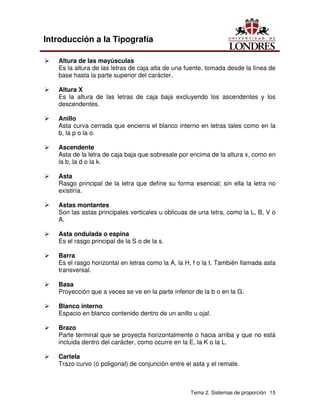
Introducción a la
Tipografía
Introducción
El significado de un mensaje ha de hablar en el interior de formas, de llenos y
vacíos construidos geométricamente, con las correcciones ópticas necesarias para
que la lectura sea clara y racionalmente comprensible.
La tipografía es un conjunto de reglas proyectuales y, sobre todo, en cuanto a
lugar de elaboración de la cultura, a través de la cual los hombres están en
condiciones de emanciparse, respecto de otras manifestaciones lingüísticas.
La lengua no es una forma, representa un contenido que es el resultado de
conflictos, también de dramas y de violencia, de encuentros y desencuentros... la
Historia.
Escribir sobre un alfabeto implica que mientras lo hacemos estamos echando
mano a él mismo para transmitir nuestras ideas. Así como los lectores lo usan
para entender lo que se dice. Se aplica un código habitual, aprendido. Estamos
habituados a verlo como herramienta donde «leer» y con el cual «escribir».
Es así que se nos hace invisible a menos que se nos muestre como presente,
haciendo notar las peculiaridades estructurales de esta o aquella letra, las
posibilidades de armónica proximidad y, más aún, las dotes de perceptibilidad, de
legibilidad, de fluidez de un texto compuesto con aquel determinado carácter.
Que el carácter tipográfico trascienda su propio valor instrumental, para
proponerse como entidad sígnica autónoma, no es una cosa nueva, por el
contrario, sobre el contenido estético – formal del signo alfabético existen tratados
históricos.
Así que este boom por el uso de la tipografía como forma no es nada nuevo.
Objetivo general
Al término del curso el estudiante transcribirá a proyectos de diseño gráfico los
principales elementos de la composición y adecuación tipográfica a partir del
análisis de sus características y procedimientos así como las necesidades del
proyecto.
Calculará y proporcionará las diferentes fuentes y familias tipográficas de acuerdo
con las necesidades de comunicación del mensaje a elaborar.
Tema 1. El tipo
Subtemas
1.1 Definición
1.1.1 Definiciones de tipografía
1.2 Elementos anatómicos
1.3 Estilos y personalidad del tipo
1.4 Clasificación
1.4.1 Familias tipográficas
1.4.2 Fuentes tipográficas
1.4.3 Series
Objetivo de Aprendizaje
Al término del tema el estudiante distinguirá lo que es un tipo, una fuente y una
familia tipográfica y entenderá su importancia en la transmisión de mensajes.
Introducción
La Tipografía como disciplina del Diseño Gráfico estudia los distintos modos de
optimizar la emisión gráfica de mensajes verbales. El diseñador gráfico en su
tarea cotidiana debe conocer las familias tipográficas para poder expresar
correctamente la idea que requiere conceptuar.
1.1 Definición
Tipo es el objeto físico, un bloque paralelepipédico de metal (aleación tipográfica)
que tiene en su cara superior, en relieve e invertida, la imagen de una letra o signo
para la impresión por sistema tipográfico.
1.1.1 Definiciones de tipografía
En nuestra tarea cotidiana, Tipografía admite cuatro definiciones:
1) La primera de ellas, referida al origen de la palabra tipografía se emplea para
designar a la técnica de impresión con tipos móviles que; procedente de Asia,
llegó a Europa a mediados del siglo XV;
Tema 1. El tipo 7
Introducción a la Tipografía
2) La segunda, impuesta por los avances tecnológicos, extiende los alcances de
la primera definición y denomina tipografía a todas las modalidades de
reproducción de palabras y textos de la actualidad;
3) La tercera, aplicada en ámbitos académicos, denomina Tipografía a la
materia en que se desarrollan los contenidos históricos, teóricos y prácticos
referidos al elemento con que se representan visualmente las palabras y los
textos.
4) La cuarta acepción es la más abarcativa, se emplea recientemente en el
ámbito profesional del Diseño Gráfico y es la que más nos interesa:
denomina Tipografía a la disciplina que dentro del Diseño Gráfico estudia los
distintos modos de optimizar la emisión gráfica de mensajes verbales. La
Tipografía tiene una dimensión técnica y funcional basada en el oficio de
tipógrafos e impresores. Cuenta con sistemas de medición y cálculo que
ayudan a organizar y racionalizar la comunicación visual. Pero tiene además
una dimensión humanística que se basa en la escritura, representación
abstracta de objetos e ideas que hizo posible el registro de la cultura, la
organización del pensamiento y el desarrollo intelectual del hombre.
Entendida como disciplina, la Tipografía profundiza y enriquece en
direcciones múltiples los alcances del Diseño Gráfico.
1.2 Elementos anatómicos
La temprana asociación entre las letras y la forma humana y sus movimientos ha
ejercido cierta influencia en el pensamiento creativo. Estas similitudes
estructurales, que tienen su origen en las leyes de la naturaleza, liberan a las
letras de su bidimensionalidad y las pone en movimiento haciéndolas participar
activamente dentro de la composición.
Hablar de anatomía del tipo es hablar de la forma de la letra, de sus detalles más
íntimos, de la manera en que cada una de sus partes ha sido moldeada y
reinterpretada a través del tiempo. Debido a que la forma de una tipografía tiene
un gran impacto sobre la función que esta cumple, es importante conocer como la
presencia o ausencia de ciertos elementos pueden afectar a una determinada
familia de tipos, y por ende al texto en el cual es usada.
Desde sus orígenes los caracteres han sufrido una constante transformación, de lo
antiguo a lo moderno, de lo sobrio a lo exagerado, de lo orgánico a lo sintético.
Durante este proceso han recibido infinidad de aportaciones, muchas veces
dependiendo del contexto histórico, político, económico y social del que formaban
parte. Es gracias a estas características que podemos clasificar las tipografías,
aun cuando surgen ciertos conflictos para llevar a cabo dicha tarea.
Tema 1. El tipo 8
Introducción a la Tipografía
La aplicación indiscriminada de términos ha provocado que el estudio de la
tipografía se dificulte, algunos conceptos han logrado alcanzar cierta
estandarización.
1.3 Estilos y personalidad del tipo
Desde fines del siglo XIX hasta principios del siglo XX, los símbolos del desarrollo
industrial y la maquinaria utilizada para su creación se expresaron vívidamente en
la arquitectura, la pintura, la fotografía, el cine y la escultura, así como en los
medios publicitarios. La influencia de esta revolución industrial y las cambiantes
orientaciones políticas estimularon el desarrollo de movimientos artísticos como el
futurismo y el constructivismo. Los artistas y los diseñadores innovadores
propagaron la creación de poderosas imágenes visuales que reflejaron el espíritu
vibrante de la época. Desde la época de Gutenberg, la fundición de tipos fue el
principal método de composición. Sin embargo, hacia fines del siglo xix, la
composición manual que utiliza tipos fundidos fue reemplazada por la introducción
de máquinas de composición tipográfica que permitían grabar los caracteres
directamente en el taller tipográfico.
Relación de la tipografía con la escritura. Influencia de los orígenes históricos de
las formas escriturales sobre las familias tipográficas modernas.
Esquema de la evolución histórica de la escritura. Cuatro fases:
- Semasiográfica
- Pictográfica
- Fonográfica
- Hipergráfica
Evolución de las formas fonográficas según un modelo (no paradigmático) de
etapas:
- Jeroglíficas
- Silábicas – Protoalfabéticas
- Alfabéticas
Evolución histórica de los alfabetos y de su uso social hasta el presente.
- Alfabetos griegos
- Alfabeto romano
- La escritura medieval
- Renacimiento e invención de la imprenta
Tema 1. El tipo 9
Introducción a la Tipografía
- Ilustración. Siglo XVIII ILUSTRACIÓN
- Litografía y composición en caliente
- Composición electrónica SIGLO XX
Familias tipográficas. División en subfamilias según el trazo, los ejes y las
proporciones.
- Superfinas, finas, medium, negras, supernegras...
- Rectas, cursivas retrógradas...
- Redondas, chupadas o condensadas, expandidas o anchas...
- Perfiladas, sombredas.
1.4 Clasificación
1.4.1 Familias tipográficas
Una familia tipográfica es un grupo de tipografías unidas por características
similares. Los miembros de una familia (los tipos) se parecen entre si, pero
también tienen rasgos propios. Las tipografías de cada familia tienen distintos
grosores y anchos. Algunas familias las forman muchos miembros, otras sólo de
unos pocos.
En resumen una familia tipográfica se define como un conjunto de letras de
cualquier tamaño y estilo que tienen el mismo diseño común. Una fuente
tipográfica (font) es un alfabeto completo dibujado en un solo tamaño y un solo
estilo.
1.4.2 Fuentes tipográficas
La palabra fuente se utiliza actualmente para describir todos los elementos
anteriores más las cursivas, finas y negras de la misma familia de tipos. Una
tipografía está compuesta por los conjuntos de caracteres representados por todos
los tamaños y grosores de una determinada clase de letra.
Cada tipo era un bloque metálico paralelepipédico de 2,5 cm de longitud que
llevaba en una de sus caras una letra o un carácter en relieve. Las líneas de tipos
se componían, se entintaban y se colocaban en la prensa de imprimir que oprimía
el tipo contra el papel u otro tipo de soporte, produciendo una imagen legible.
Aunque la época de mayor auge de los tipos metálicos y la impresión en relieve
quedó atrás hace tiempo, la palabra tipo sigue describiendo un carácter de
impresión independientemente del material, ya sea éste metal, película o soporte
Tema 1. El tipo 10
Introducción a la Tipografía
magnético, o incluso esté almacenado en forma de una serie de fórmulas
matemáticas en una computadora.
En autoedición, los términos tipografía y fuentes a menudo se confunden como
sinónimos; sin embargo, la tipografía es el diseño de caracteres unificados por
propiedades visuales uniformes, mientras que la fuente es el juego completo de
caracteres en cualquier diseño, cuerpo y estilo.
Estos caracteres incluyen letras en caja alta y baja, numerales, versalitas,
fracciones, ligaduras (dos o más caracteres unidos entre sí formando una sola
unidad), puntuación, signos matemáticos, acentos, símbolos monetarios y
grafismos (adornos variados y florituras diseñados para su uso en las fuentes)
entre otros. Aunque, para autoedición, la totalidad de los caracteres citados suelen
estar en las fuentes denominadas «expert».
1.4.3 Series
Por su naturaleza de multiplicidad estilística, la familia tipográfica serial nos
propone una manera particular de abordar el diseño de caracteres. Un repaso
sobre los diseños más influyentes, considerados en su contexto histórico, deja
abiertos algunos interrogantes y controversias para la discusión.
Demos fue diseñada en 1976 para el sistema de fotocomposición Digiset Gerard
Unger dibujó manualmente signo por signo en una matriz de 100 puntos
horizontales por 120 en vertical.
El programa de Rotis fue manufacturado por Agfa Compugraphic en 1988. Como
caracteres distintivos en el diseño en general se destacan la c y la e, esta última
por su altísima cintura.
La familia serial y la clasificación de tipos. La idea de abordar un grupo específico
de tipos dentro del vasto universo de familias tipográficas parece exigir una
justificación inmediata. De hecho, el argumento podría entenderse como el
artilugio esencial del acto -taxonómico si los hay- de clasificación de tipos: ¿Cómo
agrupar especies comparando sus cualidades constitutivas? Sin embargo, ya que
esto puede considerarse desde varios aspectos: históricos, tecnológicos o (más
frecuentemente) estilísticos, la clasificación resultante termina involucrando
también un criterio particular de aproximación al problema.
La historia de la clasificación de tipos podría pensarse de este modo como la
historia de los intentos sucesivos por organizar la variedad de formas tipográficas
desde un punto de vista innovador. Se calcula en la actualidad entre 8.000 y
11.000 el número de tipografías conocidas. Es claro que la continua aparición de
nuevas familias en ambos campos, texto y display, desestima la idea de una
Tema 1. El tipo 11
Introducción a la Tipografía
taxonomía definitiva y más bien nos lleva a pensar que la clasificación de tipos es
algo vivo que reclama un espíritu de constante revisión. Pero el título de este
artículo es también el resultado de un discernimiento particular sobre
determinadas familias tipográficas de acuerdo con su pertenencia a un pequeño
universo. Este universo parece tocar preliminarmente conceptos como: familia,
subfamilia y superfamilia, interrelación, declinación, alternación, programa, serie.
Sería posible decir, sin embargo, que esos conceptos son inherentes al diseño de
toda tipografía, desde que cada letra individual es como una nota en armonía con
el resto de la melodía o, en palabras de Sumner Stone, «una variación sobre un
paso de danza básico». Aunque más aparente, este aspecto, sutil herencia de la
mano de calígrafos y escribas, es aún constitutivo del diseño de tipos en términos
de ritmo y uniformidad: cada signo ha sido construido por la misma herramienta o,
al menos, existe un principio común que gobierna la consistencia formal de todo el
alfabeto.
Tema 1. El tipo 12
Introducción a la Tipografía
Resumen
El tipo básicamente es un caracter de impresión, una tipografía está compuesta
por los conjuntos de caracteres representados por todos los tamaños y grosores
de una determinada clase de letra los cuales son indispensables en el diseño
gráfico. Los tipos se pueden clasificar en fuentes, familias y series, para lograr
estas clasificaciones nos vamos a aprovechar de sus rasgos característicos y
estilos.
Conclusión
La clasificación de los tipos y sus características nos va ayudar a identificarlos y
poder expresar la idea o mensaje que queramos o necesitemos.
Tema 2. Sistemas de proporción 13
Introducción a la Tipografía
Tema 2. Sistemas de proporción
Subtemas
2.1 Concepto
2.2 Estructura
2.3 Módulo X
2.4 Light, bold, espesor
2.5 Romanas e itálicas
Objetivo de Aprendizaje
Al término del tema el estudiante conocerá las diferentes partes de una letra
Introducción
Es importante conocer los sistemas de proporción y la terminología que hace
referencia las diferentes partes de una letra.
2.1 Concepto
Los sistemas de proporción nos van permitir construir una tipografía a partir de
un tipo y sus características para esto vamos a tener que tomar en cuenta ciertos
elementos que veremos a continuación dentro de este capítulo.
Lo más importante de la elección de cualquier medida tipográfica es que esté en
relación con las que ya se han tomado o tienen que tomarse.
Ninguna medida tipográfica es independiente de las otras.
• Del tamaño del cuerpo depende la línea
• De la longitud de la línea depende la interlínea
• De las interlíneas depende la coherencia del párrafo, etc
Hay que considerar, además, que muchos diseños tipográficos requieren un
particular tratamiento, al cual el diseñador tiene que ser sensible.
• Algunas familias requieren ser usadas en cuerpos grandes porque si no, no
se aprecia su diseño
Tema 2. Sistemas de proporción 14
Introducción a la Tipografía
• Lo mismo al contrario: letras de proporciones estrechas, muy espigadas,
pueden ser fatigosas cuando se usan a razón de 150 caracteres en líneas
que tal vez no son demasiado largas, pero que cansan al lector. La
proporción del diseño de la letra y de la línea, no cuadran entre sí.
2.2 Estructura
El vocabulario usado para la descripción de las diferentes partes que estructuran
una letra, se compone de una serie de términos acuñados desde hace mucho
tiempo y que se asemejan a los usados para describir las partes de nuestro
cuerpo. Así las letras tienen brazos, piernas, ojos, y otras partes como cola.
De cualquier forma, por problemas de traducción, la descripción de las partes de
una letra no coinciden de forma unánime en los libros sobre tipografía y diseño. En
todo caso los términos que aquí se reflejan constituyen un buen bagaje para
comprender y conocer las distintas partes de una letra.
Tema 2. Sistemas de proporción 15
Introducción a la Tipografía
Ü Altura de las mayúsculas
Es la altura de las letras de caja alta de una fuente, tomada desde la línea de
base hasta la parte superior del carácter.
Ü Altura X
Es la altura de las letras de caja baja excluyendo los ascendentes y los
descendentes.
Ü Anillo
Asta curva cerrada que encierra el blanco interno en letras tales como en la
b, la p o la o.
Ü Ascendente
Asta de la letra de caja baja que sobresale por encima de la altura x, como en
la b, la d o la k.
Ü Asta
Rasgo principal de la letra que define su forma esencial; sin ella la letra no
existiría.
Ü Astas montantes
Son las astas principales verticales u oblicuas de una letra, como la L, B, V o
A.
Ü Asta ondulada o espina
Es el rasgo principal de la S o de la s.
Ü Barra
Es el rasgo horizontal en letras como la A, la H, f o la t. También llamada asta
transversal.
Ü Basa
Proyección que a veces se ve en la parte inferior de la b o en la G.
Ü Blanco interno
Espacio en blanco contenido dentro de un anillo u ojal.
Ü Brazo
Parte terminal que se proyecta horizontalmente o hacia arriba y que no está
incluida dentro del carácter, como ocurre en la E, la K o la L.
Ü Cartela
Trazo curvo (o poligonal) de conjunción entre el asta y el remate.
Tema 2. Sistemas de proporción 16
Introducción a la Tipografía
Ü Cola
Asta oblicua colgante de algunas letras, como en la R o la K.
Ü Cola curva
Asta curva que se apoya sobre la línea de base en la R y la K, o debajo de
ella, en la Q. En la R y en la K se puede llamar sencillamente cola.
Ü Cuerpo
Altura del paralelepípedo metálico en que está montado el carácter.
Ü Descendente
Asta de la letra de caja baja que queda por debajo de la línea de base, como
en la p o en la g.
Ü Inclinación
Es el ángulo del eje imaginario sugerido por la modulación de espesores de
los rasgos de una letra. El eje puede ser vertical o con diversos grados de
inclinación. Tiene una gran importancia en la determinación del estilo de los
caracteres.
Ü Línea de base
La línea sobre la que se apoya la altura X.
Ü Ojal
Porción cerrada de la letra g que queda por debajo de la línea de base. Si
ese rasgo es abierto se llama simplemente cola.
Ü Oreja
Ápice o pequeño rasgo terminal que a veces se añade al anillo de algunas
letras, como la g o la o, o al asta de otras como la r.
Ü Rebaba
Espacio que queda entre el carácter y el borde del tipo metálico. Aunque se
suele nombar de esta forma, la definición correcta es "hombro".
Ü Serif, patin, remate o gracia
Trazo terminal de un asta, brazo o cola. Es un resalte ornamental que no es
indispensable para la definición del caracter, habiendo alfabetos que carecen
de ellos.
Ü Vértice
Punto exterior de encuentro entre dos trazos, como en la parte superior de
una A, o M o al pie de una M.
Tema 2. Sistemas de proporción 17
Introducción a la Tipografía
2.3 Módulo X
También conocido como altura x, distancia que alcanzan sobre la línea base las
letras minúsculas que no tienen trazos ascendentes ni descendentes
2.4 Light y bold, espesor
Otra propiedad de los tipos de letra tiene que ver con el espesor (ancho o peso)
de los tipos.
El espesor proporcional se llama así porque el ancho de los caracteres es
proporcional a su figura. Se supone que este espesor es el adecuado para el texto
base.
Estos ligeros cambios de espesor combinados con la inclinación del eje dan
origen a las familias: normal, cursiva, negrita o bold, ligera o light, demi-bold, extra
light y extra bold entre otros.
Cualquiera modos de espesor puede aplicarse a los dos estilos principales de los
caracteres, la letra romana o con patines y la letra paloseco o sin patines. Para los
estilos secundarios (manuscrita y fantasía), el espesor no es importante.
2.5 Romanas e itálicas
El alfabeto latino se remonta al imperio romano aunque sus orígenes son muy
anteriores con alfabeto con el tiempo los romanos desarrollarían un alfabeto a
través del etrusco, pero usando solo 21 de las 26 letras originales. Hubo 13 letras
que no variaron respecto de la de los griegos: A, B, E, H, I, K, M, N, O, T, X, Y y Z:
otras 8 letras fueron modificadas C, D, G, L, P, R, S, V y se restauraron otras dos
letras F y Q (que habían existido en el griego primitivo, pero se habían perdido en
el clásico.) Así pues, el alfabeto romano tenía 23 letras entre vocales y
consonantes, y con el los romanos lograron escribir una representación fonética.
De su lengua que hoy llamamos latín, las 3 letras adicionales- J, U y W – son
introducciones más recientes que se realizaron para representar otros sonidos.
Los romanos usaban la “I” para representar los sonidos de la “I y de la J y de la V
tanto para representar la U como la V la W se creo para representar un sonido en
ingles antiguo. Aunque el alfabeto romano adoptó numerosas formas, la capitales
quadrata (capital cuadrada) ha ejercido la máxima influencia en el desarrollo
tipográfico y de las escrituras de inscripción.
Tema 2. Sistemas de proporción 18
Introducción a la Tipografía
A la letra que tiene el eje inclinado se le llama itálica. Este término aplica igual de
igual manera para Romanas o San Serif, es decir fuentes con patines o sin
patines.
Tema 2. Sistemas de proporción 19
Introducción a la Tipografía
Resumen
En este capitulo el diseñador conoce el vocabulario utilizado para referirse a los
diferentes componentes de una letra así como los diferentes estilos.
Conclusión
Es importante que al referirnos a la tipografía conocer los antecedentes del
alfabeto latino así como las partes que constituyen cada una de las letras.
Tema 3. Adecuación tipográfica 20
Introducción a la Tipografía
Tema 3. Adecuación tipográfica
Subtemas
3.1 Concepto
3.2 Función
3.3 Características
3.4 Texto e imagen: Integración de dos formas de comunicación
Objetivo de Aprendizaje
Al término del tema el estudiante manejará diferentes técnicas y elementos para
comunicar mensajes a partir de textos y letras.
Introducción
La tipografía es un arte sutil. Se basa en pequeñísimas variaciones aplicadas a las
formas genéricas de las letras, que llevan por nosotros más de dos mil años. El
problema es que una pequeña modificación puede resultar de enorme efecto.
También es un arte sutil porque los elementos tipográficos han de conjugar entre
sí de manera muy delicada, y es suficiente con variar unos pocos parámetros para
que el proceso de lectura o de apariencia se altere.
Hay que añadir que el principio clásico que afirmaba que la tipografía sólo tiene el
deber de ser legible ha quedado desfasado. En términos generales la tipografía
tiene en la legibilidad el principal fundamento de su existencia, pero el plano
estético y de matización del simbolismo en la comunicación han cobrado una gran
importancia con la llegada de la tipografía digital.
3.1 Concepto
La Tipografía es uno de los diversos espacios del Diseño Gráfico cuyo objetivo
primordial es la producción de comunicación a través de la letra impresa. A la vez
que el diseño tipográfico debe satisfacer los requerimientos de transmisión de
información a partir de formas visuales, con el necesario conocimiento de las
pertinentes nociones ópticas, esta disciplina depende en la práctica de la relación
que se mantiene con las también posibilidades artísticas. La Tipografía requiere a
la vez experiencias de carácter plástico, en tanto que cada proceso de
configuración se acompaña de una expresión plástica.
Tema 3. Adecuación tipográfica 21
Introducción a la Tipografía
Se acotará básicamente la primera consideración de la Tipografía, determinada
por su finalidad práctica precisa: la transmisión de información a través de formas
visuales. Nos introduciremos en uno de los fines esenciales de la obra impresa por
medio de los signos de escritura, lo que implica uno de los campos de trabajo del
diseñador tipográfico: la configuración y coordinación del texto favoreciendo su
absorción por parte del lector.
La Tipografía, aparte de su función de optimizar la transcripción gráfica de sonidos
hablados, por medio de un sistema de signos convencionales, dota de un valor
expresivo al contenido del mensaje por medio de referencias formales en una
imagen. Se parte de la idea de la necesidad de atender al paralelismo existente
entre el contenido del texto y de su revelación en el espacio visual a través del
diseño tipográfico Factores que evidencian la problemática de la expresión
tipográfica serán la influencia de las nuevas tecnologías a la producción e
interpretación tipográfica, así como la necesidad de diferenciación y competencia
de nuestra sociedad industrial como factor de gestión empresarial a través de la
expresión verbal de la Identidad Visual Corporativa (logotipo). La Publicidad es
otro apartado en el que debemos penetrar ya que sus características específicas
exigen la unidad entre la palabra y la forma. Otros aspectos a tratar, de carácter
más general (problemáticas lingüísticas, requerimientos sociales, políticos e
ideológicos, ...), determinarán también a la Tipografía en sus valores visuales y
expresivos, ayudando al conocimiento de la “historia de la forma”.
3.2 Función
Tres elementos que parecen insoslayables a la hora de diseñar tipografía:
Ü Conocer
En principio es necesario adquirir el conocimiento de los múltiples aspectos
que la escritura y los caracteres tipográficos han asumido en los diversos
períodos.
Ü Ejecutar
El estudio en profundidad de los elementos estructurales del alfabeto y de las
leyes ópticas que gobiernan el dibujo de las letras y su composición, resulta
esencial a los fines de la reproducción correcta de los caracteres.
Ü Proyectar
A partir de las formas memorizadas y gracias a una técnica de ejecución
adquirida con paciencia, pueden afrontarse temas de proyección y de
investigación para el estudio de nuevos signos aptos para una comunicación
más fuerte y duradera.
Tema 3. Adecuación tipográfica 22
Introducción a la Tipografía
3.3 Características
El principio de jerarquía
La palabra Jerarquía no está de moda. Trae a la memoria viejos tiempos de
obediencia ciega y demasiada disciplina. Pero eso poco importa: una cosa es la
jerarquía social mal entendida, y otra muy distinta la jerarquía perceptiva y de
concepto, de la cual nos servimos para conocer mejor lo que nos rodea y para
comunicarnos.
La jerarquía, en términos de lógica visual, no es otra cosa que una manifestación
de las relaciones que se producen entre las cosas que vemos y entre las cosas y
nosotros mismos.
En este capítulo trataremos de los siguientes temas:
- El campo de la jerarquía en la percepción.
- Tipos de jerarquías naturales y culturales.
- El principio de anomalía perceptiva.
- Tipos de anomalías perceptivas.
- 10 ejemplos característicos de los conceptos explicados.
- Bibliografía.
El campo de la jerarquía en la percepción
La jerarquía es un principio de valor que presenta numerosas variables y se
produce en todo tipo de circunstancias.
Desde el punto de vista de la creación gráfica, es de particular importancia cuando
se considera en relación con la información que una persona recibe, ya que el
principio jerárquico hace que valore más aquello que le afecta o es de su interés.
El ser humano dispone de unas capacidades limitadas tanto en la percepción
como en el conocimiento. Necesita tiempo para asimilar y para comprender.
Incluso tiempo para ver, aunque esto apenas lo apreciemos. Mientras esto
suceda, los valores jerárquicos actuarán como un filtro que ordena la información.
Muchos de los valores que aplicamos en nuestra relación con el exterior son
aprendidos, otros son de tipo personal y otros tantos parecen tener profundas
raíces en nuestra naturaleza. Algunos de ellos presentan una faceta
marcadamente visual. A éstos últimos les dedicaremos una especial atención.
Entre los aspectos que pueden hacer variar los valores jerárquicos de una persona
en un momento dado están los que se refieren a la atención selectiva. Es decir,
situaciones en las cuales un individuo busca o espera algo concreto.
Tema 3. Adecuación tipográfica 23
Introducción a la Tipografía
Esta atención selectiva afecta a los siguientes parámetros:
• El interés, que se desvía hacia un campo concreto.
• La situación, que es analizada con fuerte tendenciosidad por el individuo.
• Los valores, que se adaptan a las circunstancias y pueden modificarse.
Tipos de jerarquías naturales y culturales
Todo lo que nos rodea en sociedad está lleno de valores jerárquicos. Desde el
semáforo que regula el tráfico al trato especial de que goza un jefe de gobierno.
La naturaleza tampoco se libra de prioridades. Consideremos la forma de
alimentación de los polluelos en el nido o el orden en la comida de un grupo de
leones.
Muchas de estas jerarquías se asocian a patrones visuales lógicos, que usamos
sin apenas caer en la cuenta. Es lo que puede suceder al ceder el puesto en una
mesa a la hora de comer o en la configuración que adoptamos cuando van a
hacernos una fotografía.
Veamos ahora algunos de estos elementos de lógica visual que afectan o son
afectados por valores jerárquicos.
1. La jerarquía arriba / abajo
Se manifiesta como la prioridad de lo superior en el espacio o en el plano,
que presenta una conexión directa con lo superior en el orden de las ideas o
en el orden moral.
La imagen reproducida más abajo establece una jerarquía entre las letras
que tiene una de sus bases más relevantes en su posición relativa superior /
inferior.
La letra M supera en visibilidad a las
otras letras por el hecho de estar más
alta y destacar.
Para localizarla, el organismo gasta
menor cantidad de energía. Su posición
respecto los otros elementos le sirve de
base de proyección.
Tema 3. Adecuación tipográfica 24
Introducción a la Tipografía
2. Jerarquía grande / pequeño
Es una de las más utilizadas. En términos generales, abundan las situaciones
en las que el valor de las cosas es proporcional a su tamaño físico, respecto
de las cosas que hay a su alrededor. Un fenómeno que ya encontramos en el
arte egipcio, en el que se nos muestran gigantescos faraones imperando
sobre ejércitos de diminutas figurillas.
En la imagen de la
izquierda, la letra F
presenta ese dominio
faraónico sobre el resto de
las letras que la
acompañan. Esa fuerza
caracteriza el diseño y hace
que éste sea leído en un
orden determinado.
3. Jerarquía centrado / periférico
Esta jerarquía visual también es de las más utilizadas y ha sido denominada
"fuerza del centro". Tiene su primer fundamento en la estructuración simétrica
que presentan tantos seres y sucesos de la naturaleza. Una ley que
captamos y proyectamos a numerosos hechos o cuestiones de trascendencia
social.
En la imagen que presentamos,
la línea central, a pesar de su
menor tamaño, adquiere una
fuerza extra a causa de la
situación que ocupa. De la
misma manera, una persona que
ocupa el centro de una mesa un
acto social, toma para sí ese
factor de jerarquía visual.
Tema 3. Adecuación tipográfica 25
Introducción a la Tipografía
4. Jerarquía de lo contrastado
Este tipo de jerarquía visual actúa mediante un juego de choque perceptivo.
Aquello que contrasta salta hacia nosotros sin necesidad de que nosotros
vayamos hacia él. Su primitivo fundamento es el de un acto de defensa,
ligado a la exploración del medio en que nos movemos.
5. Jerarquía de lo separado frente a lo grupal.
Un viejo y desgastado chiste hacía decir a un vigilante en un fuerte del oeste
americano: "¡vienen dos mil tres indios!". A la pregunta de cómo lo sabía, su
respuesta era: "porque delante vienen tres y luego unos dos mil".
Ciertamente, eso es lo que sucede en nuestra percepción: vemos lo
separado y después el grupo. O si se prefiere, los grupos tienden a formar
unidades de mayor nivel: tres árboles y un bosque.
En la imagen reproducida aquí
junto la letra h se beneficia de
esa situación y salta hacia el
espectador como un elemento
con valor en sí mismo. El resto
es "un" bloque, pero su
complejidad formal requiere de
nosotros mucho más tiempo de
atención, que no siempre
estaremos dispuestos a dar.
Tema 3. Adecuación tipográfica 26
Introducción a la Tipografía
6. Jerarquía de lo brillante
En términos generales, todo aquello que irradia ha sido valorado por las más
diversas culturas: desde el oro hasta los atributos iconográficos de la
santidad, con sus aureolas luminiscentes.
Toda radiación tiene fuerza visual. Y casi toda fuerza visual puede traducirse
en fuerza física.
Cualidades anisotrópicas de la jerarquía visual
Los seis tipos de jerarquías básicas que hemos comentado tienen aspectos
anisotrópicos, es decir, de asimetría respecto de su comportamiento formal.
Por ejemplo: una superficie brillante en un entorno mate llamará más la atención
que la misma superficie en mate sobre un entorno brillante.
Esto es así porque la cualidad del brillo fatiga más los órganos perceptivos que la
cualidad mate, y la distinción, en tales circunstancias, se vuelve más compleja.
Cuando el brillo satura la percepción, ver una pequeña porción mate puede llegar
a no ser posible.
Un fenómeno similar de anisotropía sucede con la jerarquía de lo grande en
relación con lo pequeño. Entre varias formas pequeñas es inmediato el hallazgo
visual de una forma grande, pero no al contrario: muchas formas grandes, que
llenan el campo perceptivo de ruido formal, pueden hacer muy difícil la distinción
de un elemento pequeño perdido entre ellas.
Aplicaciones al diseño tipográfico
Las jerarquías visuales básicas ponen de manifiesto aspectos diversos de lógica
visual y son aplicables al diseño tipográfico, y de hecho son usadas muy
frecuentemente, tanto de manera consciente como inconsciente, por los
profesionales.
Los lectores de publicaciones, las personas que ven la televisión o circulan por las
calles de las ciudades, llevan en sí mismos estos criterios de lógica visual. De ahí
que, al usarlos, el diseñador, por así decir, hable un lenguaje formal conocido por
ellos. Y este es un hecho que, evidentemente, facilita la comunicación con el
público al que se dirige el mensaje.
Usar principios jerárquicos, a través de cualquiera de sus muchas variantes,
multiplica la eficacia de la comunicación sin limitar la creatividad formal o
conceptual de los diseñadores.
Tema 3. Adecuación tipográfica 27
Introducción a la Tipografía
En el diseño tipográfico, es muy recomendable, por ejemplo, para guiar la lectura
del espectador, estructurar y secuenciar la información que se le proporciona.
A continuación comentaremos algunos ejemplos, relacionados con la aplicación
del principio de jerarquía en el diseño tipográfico:
1. Primera página del Times, 1932
Se trata de la primera página del primer número del Times que vio la luz con
la tipografía Times New Roman, de Stanley Morison, uno de los mayores
éxitos tipográficos del siglo XX.
Como se aprecia, el diseño de los periódicos de la época era muy distinto del
actual. El del Times se basaba en una ausencia casi total de jerarquías
visuales, con breves encabezamientos por columnas, que remiten a tres
secciones: Defunciones, Asuntos personales y Ofertas empresariales. Para
localizar un tema, el lector no puede guiarse del sentido de la vista, debe leer
con detalle, ya que la tipografía es toda de la misma o parecida dimensión,
con un grado casi cero de jerarquía visual.
Un diseño de este tipo
necesita mucho tiempo de
lectura y mucha costumbre
en el público lector.
Además, ha de ser éste
quien seleccione los temas
de su interés, a través de
una lectura
pormenorizada.
Stanley Morison
pertenecía a la corriente
más conservadora de la
tipografía de la época y
consideraba que el texto
debía ser como el cristal
de una ventana: invisible al
lector, permitiéndole leer
los contenidos sin hacerse
notar.
En el primitivo diseño del Times no se consideraba la capacidad estructuradora
que puede tener la jerarquía tipográfica.
Tema 3. Adecuación tipográfica 28
Introducción a la Tipografía
2. Los "inventos" dada.
La cara más diametralmente opuesta a la estética conservadora en tipografía
la representaron, durante algunos años, los experimentos dada, que
quisieron ser un ataque directo a casi todos los principios de jerarquía
funcional que, en mayor o menor grado, se venían utilizando en arte y diseño
desde siglos atrás.
La mezcla de tipos, direcciones de
lectura, inclinaciones y colores, hace de
este texto dadaista un galimatías
tipográfico de difícil lectura, cuyo interés
radica, principalmente, en su apuesta
estética de ruptura.
Ciertamente, el uso contra funcional de
la tipografía, que tantas escuelas
artísticas propusieron en las primeras
décadas del siglo XX, no condujo,
contra lo que muchos creen, a ninguna
renovación de la tipográfica y, desde
este punto de vista, fueron un fracaso
radical.
3. Un periódico moderno.
Los periódicos y revistas de nuestros días hacen uso de claros principios
jerárquicos, que tienen como objetivo ayudar al lector a localizar la
información que desea.
Pueden leerse en menos tiempo que los antiguos y con mayor adecuación a
los gustos del público. Además, éste se acostumbra al diseño formal y de
contenido que le ofrece el periódico que lee habitualmente, un hecho que
contribuye a crear una relación estable entre el lector y el medio de
comunicación.
Tema 3. Adecuación tipográfica 29
Introducción a la Tipografía
Como se aprecia, la
jerarquía se crea a través
de varios parámetros
visuales basados en una
lógica visual prácticamente
intuitiva:
• Tamaño
• Altura en la página
• Anchura del texto
• Imágenes
• Color
Con estos elementos, el lector tiende a buscar la información en tres fases:
a) Primera lectura, de recorrido rápido, en la que se toma nota mental del
contenido general más importante.
b) Segunda lectura, complementaria del anterior, en la que se recurre a
entradillas y sumarios para ampliar el contenido de alguna o algunas de las
noticias captadas en la primera lectura.
c) Tercera lectura o lectura en profundidad, en la que el lector, convencido de
su interés por el tema, lee el desarrollo del mismo.
Como se aprecia, el propio mecanismo de diseño desencadena una lectura
jerarquizada de la información.
4. Jerarquía y anarquía
La tradición occidental, a lo largo de su historia, ha atravesado por varios
periodos de negación de los aspectos jerárquicos de la comunicación visual,
desarrollando estilos rompedores o chocantes para la creación de formas.
Tema 3. Adecuación tipográfica 30
Introducción a la Tipografía
Al comienzo de estos comentarios
hablamos de la escuela Dada.
Posterior en algunas décadas fue
la tendencia psicodélica, uno de
cuyos carteles reproducimos aquí.
La dificultad de lectura no requiere
comentario. La idea del diseñador,
Lee Conklin en este caso, 1967,
era crear una imagen impactante,
acorde con una filosofía vigente
en un sector de la juventud, al que
se dirigía.
Hay que observar, sin embargo,
que para enviar el mensaje
comercial que, en el fondo,
subyace en este cartel que
anuncia un concierto de Procol
Harum y Santana, recurre a los
métodos tradicionales de
ordenación y tamaño, como se
aprecia en los pequeños textos al
pie de la reproducción, donde aún
puede leerse con tipografía
normal: TICKETS.
5. La jerarquía en el detalle
Esta cabeza de revista fue diseñada por Herb Lubalin y en ella se aprecia el
uso de una anomalía semántica para la creación de una zona jerárquica de
significación.
Tema 3. Adecuación tipográfica 31
Introducción a la Tipografía
Las letras "i" "l" "i" son transformadas en miembros de un grupo familiar,
cambiando el diseño de la tipografía normal.
Aprovechando el interés que este cambio produce en el lector, la zona es
utilizada para insertar los rótulos editoriales: "A Reader's Digest Publication".
Lógica visual y economía de medios se unen en este diseño.
6. Jerarquía en la Web
La red está llena de páginas sofisticadas y confusas, que reclaman nuestra
atención con animaciones, parpadeos y colores brillantes. En medio de
tantos reclamos, el internauta no tiene más remedio que intentar "pasar" de
ellos, centrando su atención en lo que realmente busca o le interesa, aunque
a veces tarde demasiado en descubrirlo, o incluso se le nieguen las
oportunidades para hacerlo.
En medio de tanto ruido se agradecen
páginas con la claridad de ideas que
expresa la de Louise Nevelson: una bella
imagen que acompaña al número exacto
de textos necesarios para transportarnos a
otros tantos lugares.
Su lógica visual es la de la sencillez y el
pragmatismo: elementos separados que
no compiten entre sí y que con un mínimo
de energía gráfica nos indican las
opciones que tenemos.
Puede haber quien lo llame arte mínimo,
pero también es eficacia máxima.
3.4 Texto e imagen: Integración de dos formas de comunicación
La relación de la imagen y la letra se remonta al inicio de la escritura. Las formas
icónicas la preceden, pero la escritura se incorpora a ellas con una funcionalidad
bien definida desde el comienzo.
Tema 3. Adecuación tipográfica 32
Introducción a la Tipografía
La imagen reproducida o técnica,
contra lo que se suele creer, tiende a
ser más abstracta que la palabra.
Por ello:
- La imagen muestra y enseña.
- La palabra narra y explica.
La imagen se acomoda bien al mundo de los símbolos genéricos y representativos
debido a varias de sus propiedades:
- Su carácter analógico, que proyecta relaciones.
- Su adecuación a la representación del espacio y la forma.
- Su presencia en el mundo onírico: ambigüedad.
- Sus posibilidades de estructuración secuencial
- La rapidez con que transmite el mensaje
La palabra escrita se acomoda al mundo del relato, el desarrollo y la
argumentación debido a varias razones:
- Su dependencia del lenguaje oral.
- Su existencia lineal en el tiempo.
- La versatilidad de su gama de significados (semántica).
- La versatilidad estructural de su sentido lineal.
- La profundidad de sus conceptos.
- La mayor lentitud en la comunicación
Imágenes y letras generan estructuras mixtas de fuerte carácter. Su fuerza radica
en combinar rapidez de entrada con profundidad de contenidos.
- Existen combinaciones atípicas
- Y altamente funcionales
Tema 3. Adecuación tipográfica 33
Introducción a la Tipografía
a) Atípica, como creación estética
b) Funcional, como elemento visual y semántico de un gráfico
Tema 3. Adecuación tipográfica 34
Introducción a la Tipografía
Resumen
La adecuación, jerarquía, integración de la tipografía debe estar en función del
mensaje que se quiera comunicar.
Conclusión
Podemos valernos de la tipografía y de su manejo para poder hacer llegar más
claramente y jerarquizar los mensajes escritos.
Tema 4. Composición tipográfica 35
Introducción a la Tipografía
Tema 4. Composición tipográfica
Subtemas
4.1 Terminología
4.2 Formas
4.2.1 Estructuras reticulares
4.2.2 Construcción y reconstrucción
Objetivo de Aprendizaje
Al término del tema el estudiante conocerá la importancia de la composición de un
texto a fin de invitar a su lectura. El uso del interlineado y el interletraje a fin de
transmitir adecuadamente un mensaje.
Introducción
Para realizar cualquier trabajo gráfico el diseñador debe tener en cuenta que es lo
que va a diseñar, con que objetivo y para quien lo va a hacer ya que de esto
dependerá el espacio que existirá entre una palabra y otra, inclusive entre las
letras o caracteres de cada palabra, así como que el tipo y el color se escogerá
para transmitir el mensaje.
4.1 Terminología
Elementos básicos de la composición tipográfica;
1. La letra
A a B b C c
2. La palabra
Ejemplo Ejemplo
Tema 4. Composición tipográfica 36
Introducción a la Tipografía
3. La línea y la paleta tipográfica
Esto es una prueba con texto ciego que no merece la pena
leer para ver los resultados que se consiguen con ligeras
variaciones. Esto es una prueba con texto ciego que no
merece la pena leer para ver los resultados que se consiguen
con ligeras variaciones. Esto es una prueba con texto ciego
que no merece la pena leer para ver los resultados que se
consiguen con ligeras variaciones.
4. La columna y la retícula
El uso de la tipografía presenta dos campos específicos: el funcional y el
icónico. Ambos pueden funcionar en conjunto o separadamente.
4.2 Formas
4.2.1 Estructuras reticulares
Un juego de tipos del mismo diseño se conoce como "fundición". Los tipos se
almacenaban en cajas con las minúsculas en las cajas de abajo y las mayúsculas
en las cajas de arriba. En consecuencia, las letras minúsculas se llamaron letras
de caja baja y las mayúsculas, letras de caja alta.
Después se reunieron las letras para formar palabras en una regleta.(una guía),
una vez que creaban la linea se transfería a una galerada. Una vez estaba
completa la galerada se hacía una impresión de control. Esta impresión se llamab
Tema 4. Composición tipográfica 37
Introducción a la Tipografía
Galerada. Cada caracter se sacaba de un bloque de metal o madera y estos
bloques se colocabn uno junto al otro para crear palabras y textos. Si se requería
espacio entre las líneas, se insertaba una tira de plomo. La tira se conoce como
interlínea, término que aún se designa al espacio entre las líneas de un texto.
Cada letra tiene sus propias características. Si se mira una linea de tipos de con
los ojos entrecerrados, (método muy utilizado hoy en día) sólo se ve una banda de
tono gris. Cuando se indican caracteres en una composición, se indica esta masa
tipográfica con dos líneas paralelas o con una franja gris o con una serie de
comillas. (actualmente utilizamos el ioioioioio que simula una franja de texto).
Ejemplo:
ioioioioioioio
ioioioio.
ioioioioioioio
ioioioioioio.
Las minúsculas pueden especificarse describiendo tres elementos, la altura (X),
los ascendentes y los descendentes.
La altura x es la altura del cuerpo de la tipografía, de una minúscula, el
ascendente es un rasgo de la tipografía como el término lo dice asciende del
cuerpo de la tipografía, tomemos como ejemplo la d, f, l, etc, y los descendentes
como la j, g, p, etc.
Las mayúsculas, caja alta, se especifican como altura mayor, y estas letras más
grandes son casi siempre de la misma altura que los ascendentes de las
minúsculas.
4.2.2 Construcción y reconstrucción
Normas de composición
Desde los tiempos de la invención de la imprenta, la mayor parte del material
impreso ha sido destinado a la lectura continua y, es por esto, que lo que vamos a
tratar en este artículo son los factores fundamentales que como el tamaño del
cuerpo, el espacio entre las palabras, el interlineado y la longitud de la línea,
intervienen en la correcta disposición del material tipográfico en la composición
ordinaria o seguida orientada principalmente a su aparición en libros, que es el
Tema 4. Composición tipográfica 38
Introducción a la Tipografía
campo clásico que utilizamos a la hora de mostrar los recursos de la tipografía. En
otro, posterior, se tratará de la composición del texto destinado a titulares.
El espaciado entre las palabras
Un signo claro, presente desde los primeros tiempos de la imprenta hasta el día de
hoy, de una buena impresión y, por extensión, de un buen impresor ha sido el
cuidado y la atención dedicadas a la composición del texto ordinario. Si
examinamos de cerca los mejores trabajos de los más afamados impresores
desde mediados del siglo XV, nos encontramos con un denominador común que
es el espaciado estrecho que aplicaban entre las palabras del texto. Ante este
hecho nos podríamos preguntar Àporqué las mejores imprentas han continuado
con esta tradición durante más de quinientos años? Y Àporqué sobrevive todavía?
Buscando la respuesta en el pasado, antes de la invención de la imprenta la
escritura era la única forma de conservar y transmitir el pensamiento humano. Así
los primeros impresores vieron la oportunidad de lucrarse reproduciendo en masa
los libros realizados hasta entonces por los escribas. Naturalmente basaron sus
tipos en los de los manuscritos existentes en la época e hicieron su trabajo a
conciencia reproduciendo en metal la multitud de ligaduras y contracciones que los
escribas incluían en el texto. Además de esto, procuraron también, al componer
las páginas, copiar el hermoso espaciado estrecho entre las palabras de los
manuscritos. Y esta tradición, iniciada en los inicios de la imprenta, se ha
transmitido hasta nosotros.
Para responder a la pregunta de porqué sigue vigente se pueden enumerar dos
razones principales: la primera de ellas es eminentemente práctica y hace
referencia a la facilidad de lectura que proporciona un texto compuesto con un
espaciado estrecho entre las palabras frente a otro con un espaciado mayor entre
las mismas.
Efectivamente, los niños aprender a leer primero letra a letra, más tarde silaba a
silaba y después palabras individuales. Pero la persona adulta lee grupos de
palabras en vez de palabras individuales una a una y si para la lectura de un niño
es deseable un mayor espacio entre las palabras así como un mayor interlineado,
para un adulto esto supondría una lectura más lenta y menos eficaz ya que el flujo
lector se vería constantemente interrumpido por el excesivo blanco entre las
palabras.
La segunda razón es de tipo estético y tiene que ver con el color tipográfico de la
línea y de la gran mejora que para el mismo supone el espaciado estrecho entre
las palabras. Una página de texto cuidadosamente compuesta aparece
configurada como una serie de tiras negras separadas por canales de espacio
blanco. A la inversa, una página compuesta sin prestar atención se nos presenta
como una conjunto gris formada por multitud de manchas aisladas unas de otras,
Tema 4. Composición tipográfica 39
Introducción a la Tipografía
y esto es consecuencia de un mal espaciado entre las palabras. Como he citado
antes el flujo normal de lectura izquierda-derecha se ve ralentizado además de
que las letras cortas, esto es las que carecen de ascendentes y descendentes, y
los remates de las mismas, en el caso de que los tuvieran, no cumplen una
función primordial en la lectura como es la de guiar al ojo a lo largo de la línea. El
ojo tiende a confundirse por el énfasis vertical inducido por el relativo aislamiento
de las palabras y remarcado por los trazos ascendentes y descendentes de las
letras. Asimismo este énfasis vertical se ve incrementado por los molestos ríos o
calles que inseparablemente acompañan al texto así compuesto.
En un texto compuesto de una forma más juiciosa esta sensación de énfasis
vertical desaparece totalmente, y el espaciado estrecho entre palabras asegura
que el espacio blanco aparezca de forma preferente entre las líneas que es donde
realmente demuestra su eficacia como ayuda a la lectura. Y sobre este tema han
hablado muchas voces autorizadas:
Edward Johnston, en su clásico, Writing, Illuminating and Lettering escribió:
"La línea, especialmente en los libros manuscritos, es realmente lo más importante
de la página ya que una correcta disposición de la caligrafía depende del correcto
tratamiento de la línea y lo que procura la distinción y elegancia de las líneas de
los viejos manuscritos es:
• La aparente unión de las letras en la línea, propiciada por unos remates
gruesos.
• Su correcto funcionamiento conjunto.
• El espaciado suficiente de las líneas.
La escritura más hermosa presenta generalmente una gran ventaja sino está
demasiado abigarrada, y es más fácil hacer dificultosa la lectura juntando las
líneas unas con otras que por estrechar el espacio entre las palabras".
El gran impresor Sir Emery Walker, socio fundador junto con T. J. Cobden-
Sanderson de la famosa Doves Press, dijo, en una conversación mantenida con el
tipógrafo Bernard Newdigate:
"Las cajas de los espacios gruesos de los cajistas deberían estar llenas de
espacios finos. El resultado sería un espaciado más estrecho y libre de esos "ríos"
que desfiguran muchos impresos actuales".
La editorial Penguin Books en sus Reglas de composición, elaboradas por Jan
Tschichold en 1948 proporciona estas instrucciones a sus cajistas: "Toda
composición de texto debe llevar el espaciado entre palabras más estrecho que
sea posible. Como regla general, el espacio utilizado debe ser del tamaño
Tema 4. Composición tipográfica 40
Introducción a la Tipografía
mediano o del grosor de una "i" del tamaño de tipo usado. Espaciados más
amplios serán estrictamente evitados. Las palabras pueden ser partidas de forma
discrecional con el fin de evitar un espaciado ancho, ya que partir las palabras es
menos dañino para la apariencia de la página que disponer un espaciado ancho
entre ellas".
El espaciado correcto entre las palabras variará un poco de acuerdo con el tipo y
tamaño elegido así como por la anchura del ojo medio pero se puede dictar como
norma general que este será de 1/3 de cuadratín.
La determinación de la longitud de la línea
En la composición de texto continuo habrá de prestarse especial atención en lo
referente a la longitud de la línea a que la medida de esta no cause fatiga en el
lector y que no le presente dificultades para posicionarse en el inicio de la
siguiente línea.
Hay que tener en cuenta que cuanto mayor sea la longitud de la línea mayor será
el trayecto que debe describir el ojo y mayor será, a su vez, la dificultad para
encontrar el inicio de la siguiente línea. Pero tampoco hay que llegar el extremo
contrario donde una línea demasiado corta demanda un frecuente cambio de
dirección en el movimiento de los ojos con el consiguiente cansancio de los
mismos.
Tradicionalmente se considera una buena medida de longitud de línea la que está
compuesta por una media de 40 a 60 caracteres (incluidos los espacios) o 10 a 12
palabras, pero la consideración final estará determinada por los siguientes
factores:
El tamaño del tipo
Obviamente en una composición sólida, esto es sin espacio interlineal, es un
factor importante en la medida de la línea. Así si el tamaño del tipo se incrementa
también se incrementará la longitud de la línea y al contrario si se reduce la
longitud disminuirá.
El ojo medio del tipo
Si el tipo posee un ojo medio (altura-X) ancho, como Baskerville, su composición
será mejor apreciada en una medida más larga que si fuera un tipo con un ojo
medio condensado como Fournier.
Tema 4. Composición tipográfica 41
Introducción a la Tipografía
El diseño del tipo
Los tipos antiguos como Bembo, Garamond o Caslon permiten una mayor libertad
a la hora de establecer la medida de la línea que los tipos modernos como Bodoni
o Walbaum. En tipos de este grupo el contraste extremos entre los trazos gruesos
y finos y la finura de sus remates tienden a deslumbrar y cansar al ojo.
Los tipos sin remates, sobre todo aquellos sin modulación (aparente) en sus trazos
como la Futura de Paul Renner, tampoco parecen los más aconsejables para
composición de textos largos debido a la monotonía de sus trazos, aunque los de
concepción humanista como por ejemplo el tipo Gills Sans que diseñó Eric Gill,
pueden funcionar, y de hecho lo hacen, perfectamente en este tipo de
composición. En cualquier caso en la composición de texto con los tipos modernos
y sans serifs la medida de la línea no debe de ser excesivamente larga y además
deberá añadirse siempre un espacio entre líneas mayor.
La naturaleza y escala del trabajo
La respuesta a preguntas como ¿Qué estamos diseñando? ¿Con qué finalidad?
¿Quiénes serán sus lectores? nos dará la clave de cómo debemos enfocar el
trabajo. Indudablemente no es lo mismo una novela que un diccionario, una
enciclopedia que un libro para niños. Cada destinatario y cada uso tendrán su
contrapartida en el tipo utilizado, tamaño del mismo, longitud de la línea, etc.
Tema 4. Composición tipográfica 42
Introducción a la Tipografía
Resumen
El color, interlineado, espacio y altura de las letras, la combinación de altas y bajas
juegan un papel importante en la composición tipográfica por lo que el diseñador
gráfico no puede dejar de tomar en cuenta estos aspectos al momento de realizar
un texto.
Conclusión
Es importante tener en cuenta los tipos de letra que se van a utilizar así como el
grosor de esta ya que un efecto mal utilizado puede cansar al lector y causar
exactamente el efecto contrario de lo que se quiere lograr.
Tema 5 Cálculo tipográfico
Subtemas
5.1 Definición
5.2 Consideraciones previas
5.3 Procedimientos
5.4 Formación de una palabra
5.5 Formación de una línea
5.6 Columnas tipográficas
5.7 Características de la mancha tipográfica
5.8 Legibilidad y leibilidad
Objetivo de Aprendizaje